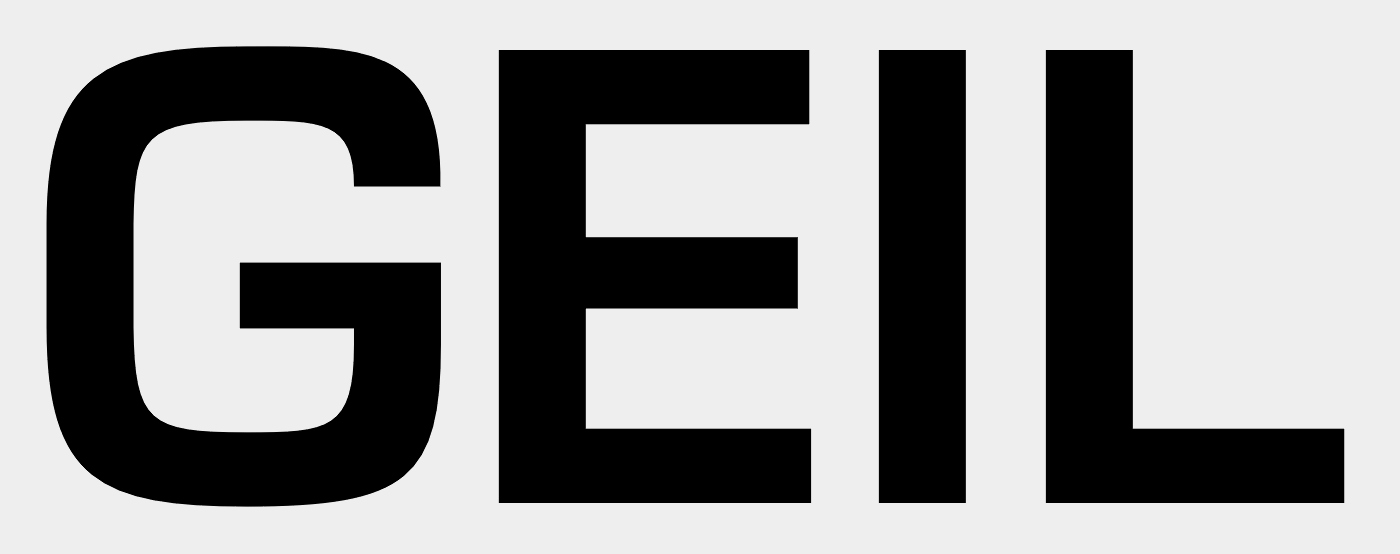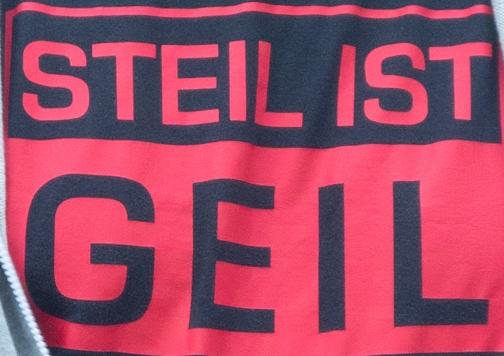
Passenede Schriftart gesucht
Vor Jahren wurde für uns ein T-Shirt mit unten stehenden Aufdruck erstellt. Leider ging die Vorlage verloren :-(.
Jetzt versuchen wir diese zu rekonstruieren, scheitern jedoch bei der Schriftart.
Diese scheint nach unseren Erkenntnissen vergleichbar mit „Arial Bold“ oder „Liberation Sans Narrow Bold Condensed“. Hundertprozentig passen diese Schriftarten aber nicht.